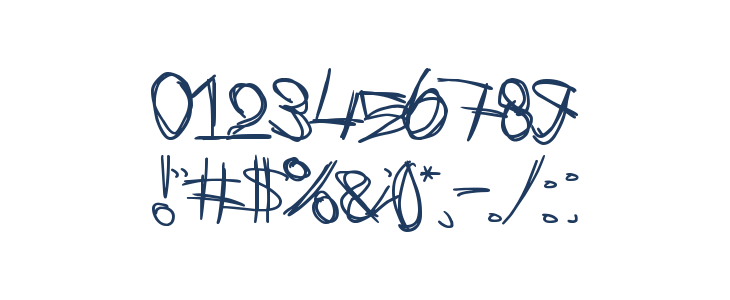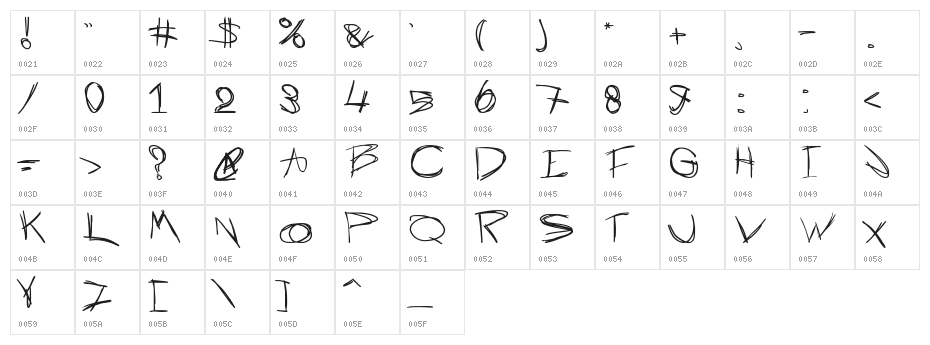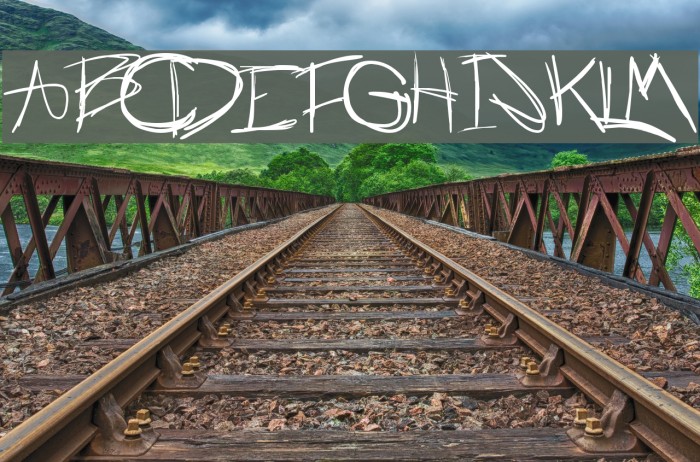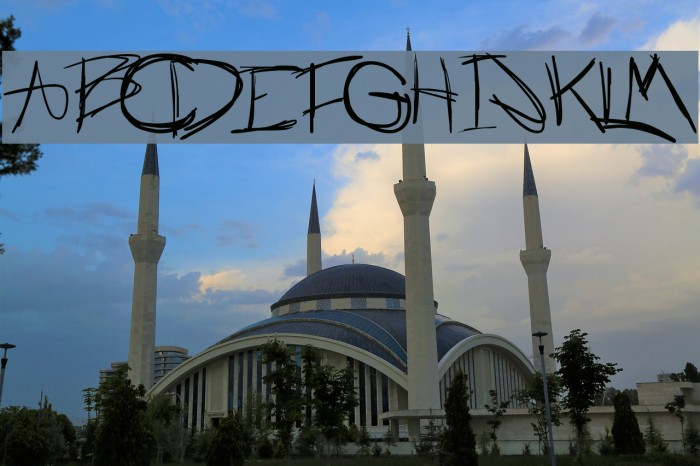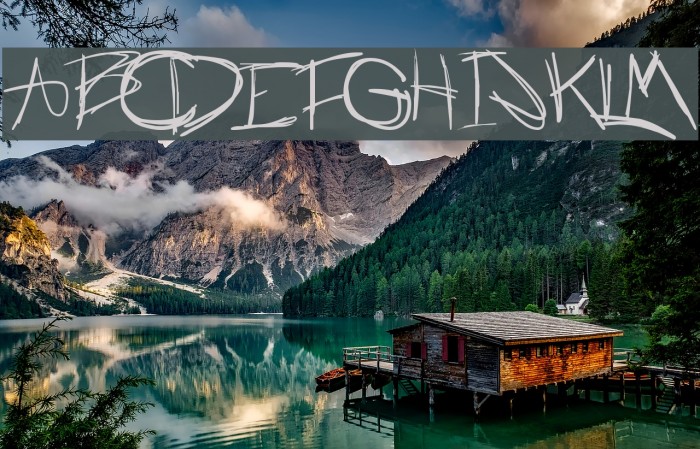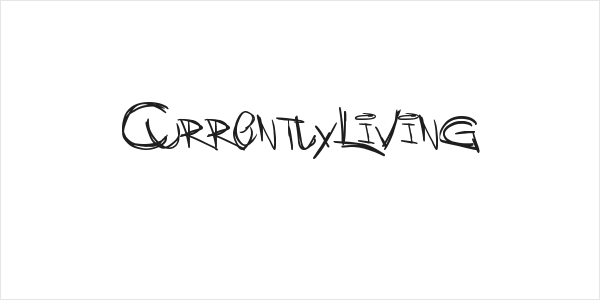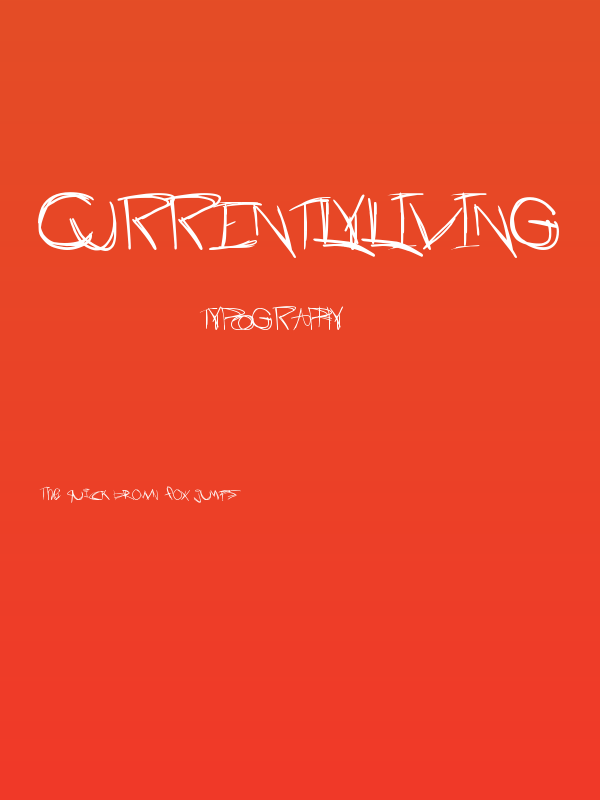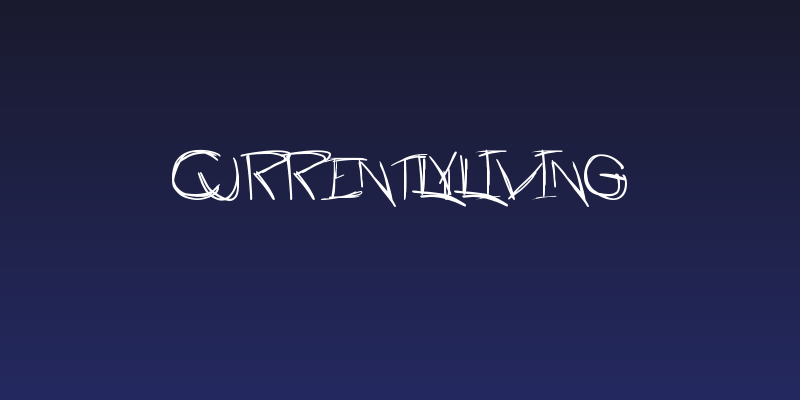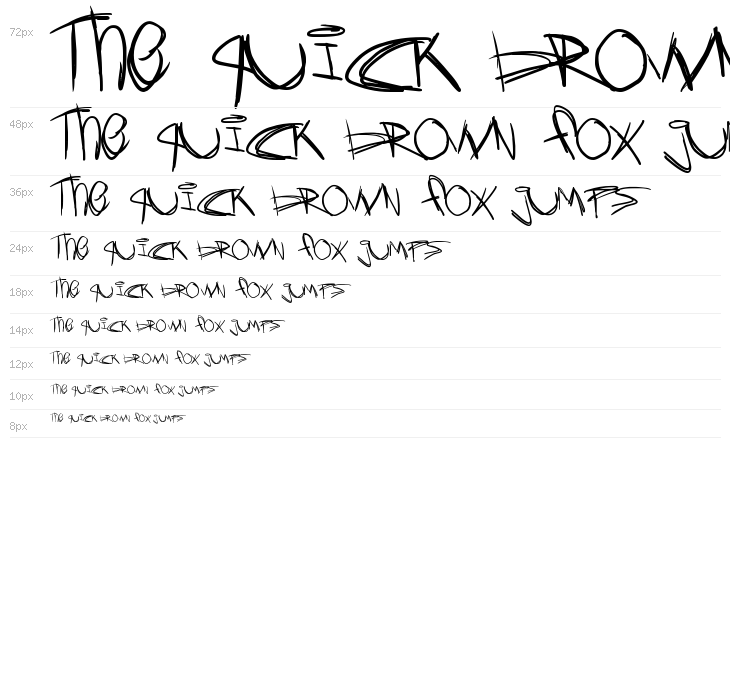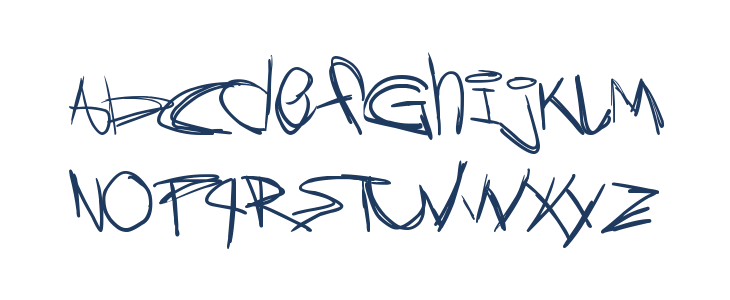
CurrentlyLiving Font
| Stile generale | Modern, Urban |
| Progetti proposti | Ideal for street art designs, edgy posters, album covers, and urban-themed branding. |